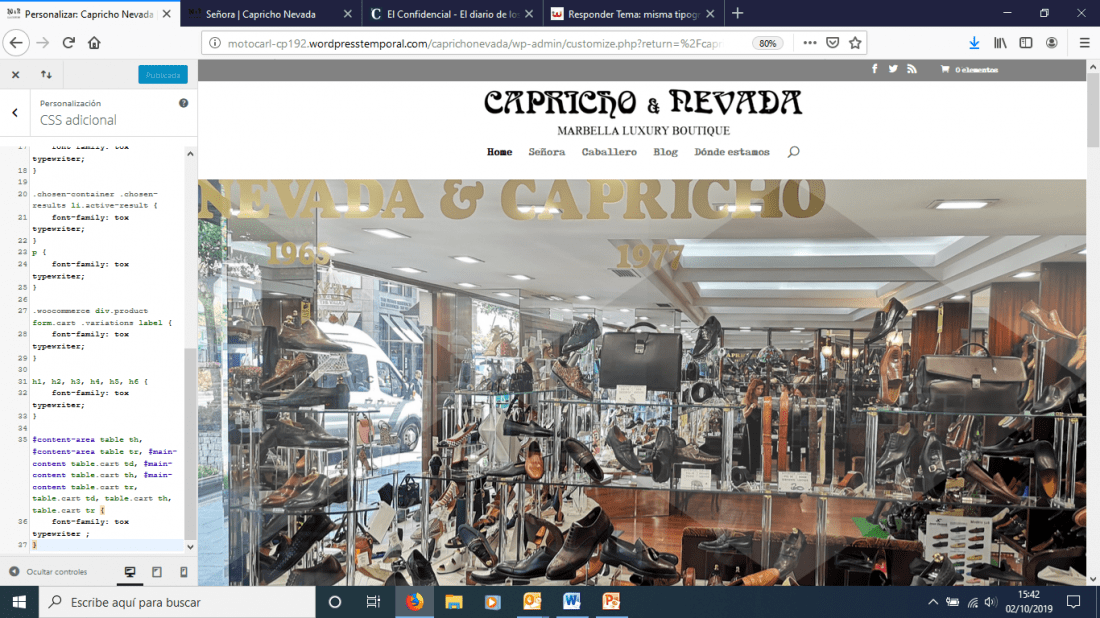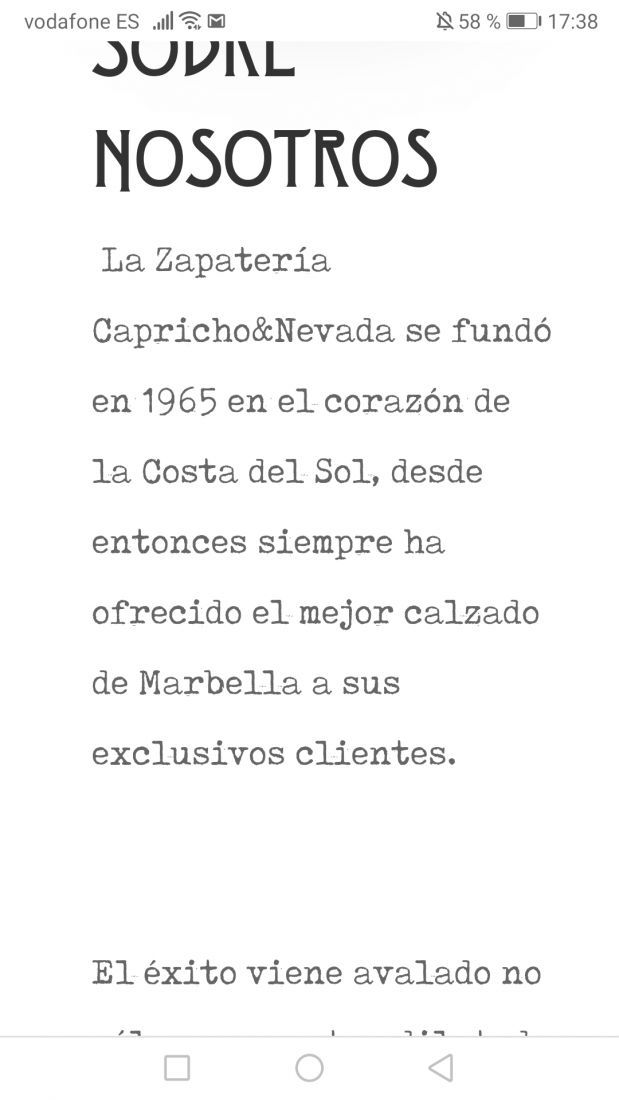
misma tipografia en toda la web
Estoy haciendo una tienda online en la que he puesto una tiipgrafía en casi todos los sitios pero en los productos, una vez que me meto en ellos, no sale esta tipografía.
¿Cómo puedo hacer para que salga en toda la web, incluida los productos y en los widgets? Les mando enlace donde aparece uno de los productos con la tipografía que quiero cambiar y los filtros de la derecha que me gustaría cambiar también, por si no me explico bien! 🙂 Me gustaría que apareciese con la tipografía Fox Typewriter como aparece en los cuerpos de texto del resto de web.
los filtros de la derecha que me gustaría cambiar
.chosen-container-single .chosen-single span {
font-family: tox typewriter;
}
.chosen-container .chosen-results li.active-result {
font-family: tox typewriter;
}
¿Cómo puedo hacer para que salga en toda la web, incluida los productos y en los widgets?
p {
font-family: tox typewriter;
}
.woocommerce div.product form.cart .variations label {
font-family: tox typewriter;
}
h1, h2, h3, h4, h5, h6 {
font-family: tox typewriter;
}
#content-area table th, #content-area table tr, #main-content table.cart td, #main-content table.cart th, #main-content table.cart tr, table.cart td, table.cart th, table.cart tr {
font-family: tox typewriter ;
}
Es posible que me deje algo, si es así adjuntar una captura de los textos que faltan y lo revisamos.
muchas gracias por la respuesta. Lo he puesto en el css pero no me cambia nada....te paso pantallazo tanto del css como de capturas de imagen de los sitios donde debería cambiarse y sigue la tipo igual.
Veo que se muestra con nuevo el tipo de letra:
Revisa accediendo en modo incognito por si el problema fuera por la cache del navegador:
Para que salga la misma tipografía en toda la web pero en versión movil tengo que hacer algo? Puse el código que me disteis para cambiar la tipografía en todo y se me ha cambiado correctamente pero en la versión móvil me sale la tipografía antigua.
No, no tienes que hacer nada, en principio es lo mismo para la versión móvil que para al de PC.
Lo estoy viendo y veo que se muestra bien:
Prueba desde otro terminal distinto.
Yo quiero que salga Tox Typewriter y la que me mandas en el pantallazo no es tipo máquina de escribir, por eso os preguntaba...gracias!
Veo que si que está cargando:
Si hay alguna parte que veas que no se muestra con el tipo de letra que quieres por favor adjunta una captura para que veamos a que haces referencia.
Te mando pantallazo donde aparece la tipografía diferente a la Tox Typewirter (máquina de escribir) . El tercer pantallazo es un ejemplo de cçomo megustaría que quedase el tipo de letra en toda la página en versión mçovil que es lo que me está fallando...he borrado el historia y cache en el teléfono y sigue saliendo diferente letra.
Faltan algunos elementos que aplicarle los estilos, aunque pueden ser un poco complicado identificarlos, agrega los siguientes estilos CSS:
.orderby, .woocommerce div.product form.cart .variations td select{
font-family: 'tox typewriter' !important;
}
El resto de contenido veo que está cargando correctamente con tox typewriter. Si identificas algun otro hazlo saber indicando la dirección web, por favor.
Buenos días,
Muchas gracias, ya lo he puesto, he borrado historial, cookies y caché en el teléfono y sigue saliendo la tipografía diferente a la tox typewriter. Me he descargado mozilla también en el teléfono para ver si era problema del navegador y tampoco sale la tipografia que he elegido, algo debo estar haciendo mal, verdad??
font-family: 'tox typewriter' !important;
font-style: oblique !important;
}